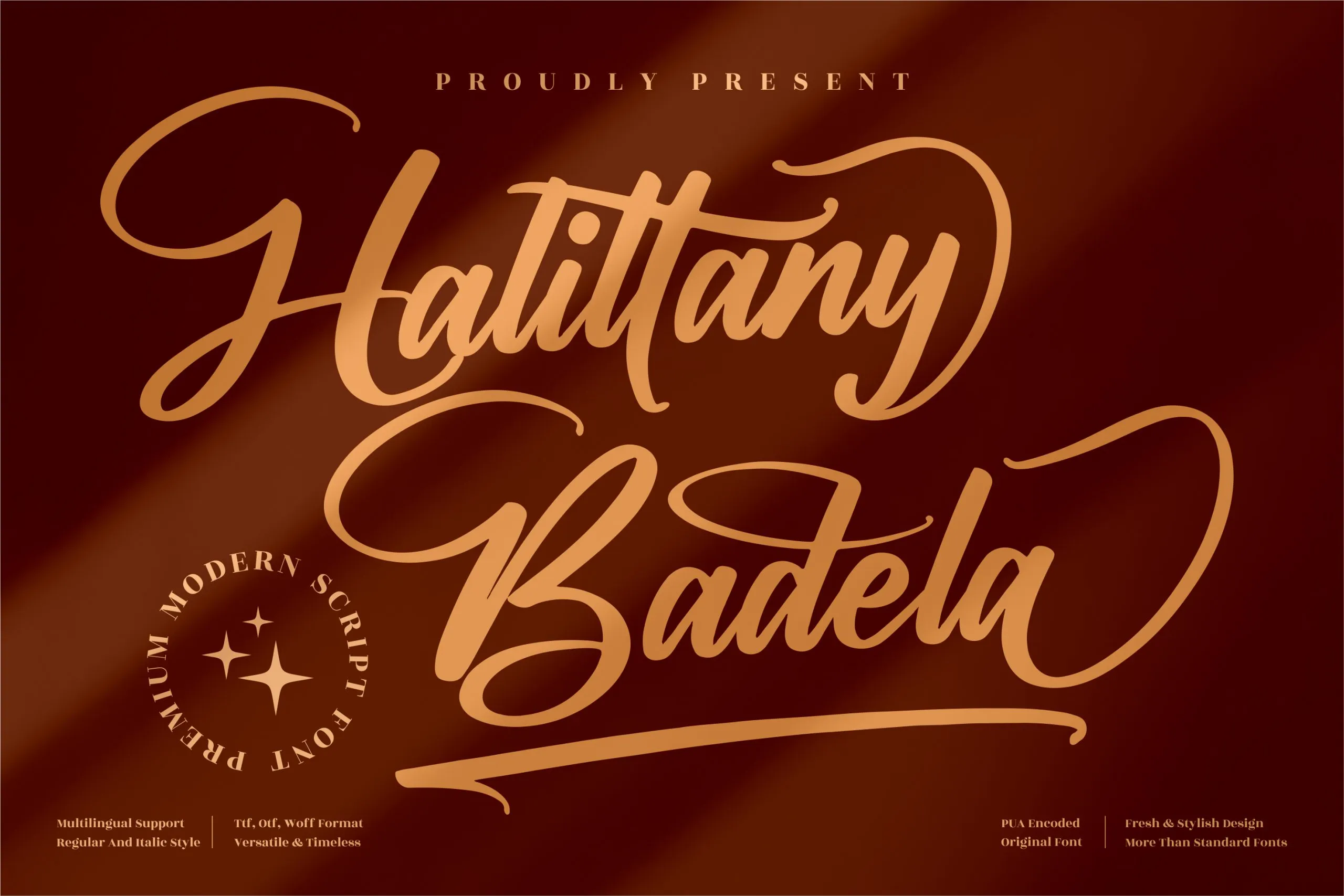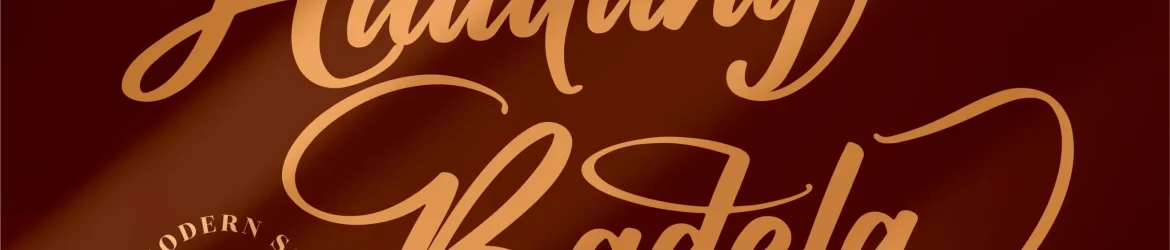
Esta fonte de gravação é ideal para quem busca personalidade e elegância para projetos que valorizam a premiumização do design. Com seu estilo refinado e detalhado, a Halittany Badela oferece uma experiência única que complementa perfeitamente desde logotipos até cartões de visita, passando por embalagens de produtos e revistas. A sua qualidade impressionante torna-a um recurso imprescindível para qualquer projeto que valorize um toque especial e um toque pessoal. Ideal tanto para designers digitais quanto gráficos profissionais, a Halittany Badela é uma escolha acima da média para aqueles que buscam se destacar em seus projetos de design.